【リコーPFUコンピューティング株式会社のご紹介】 リコーPFUコンピューティング株式会社は、MS 明朝、MS ゴシックを作ったフォントファウンダリーです。両書体は1992年に初めてWindowsに搭載された日本語TrueType Fontで、その後さまざまな進化をしながら現在もWindowsやOfficeソフトの標準フォントとして使われています。HGの付く書体が目印です(HG創英角ポップ体など)。 |
【リコーフォントの基本コンセプト】
・読み易いこと
・見やすいこと
・人に優しいこと
・使用機器のデザインや用途とマッチングすること
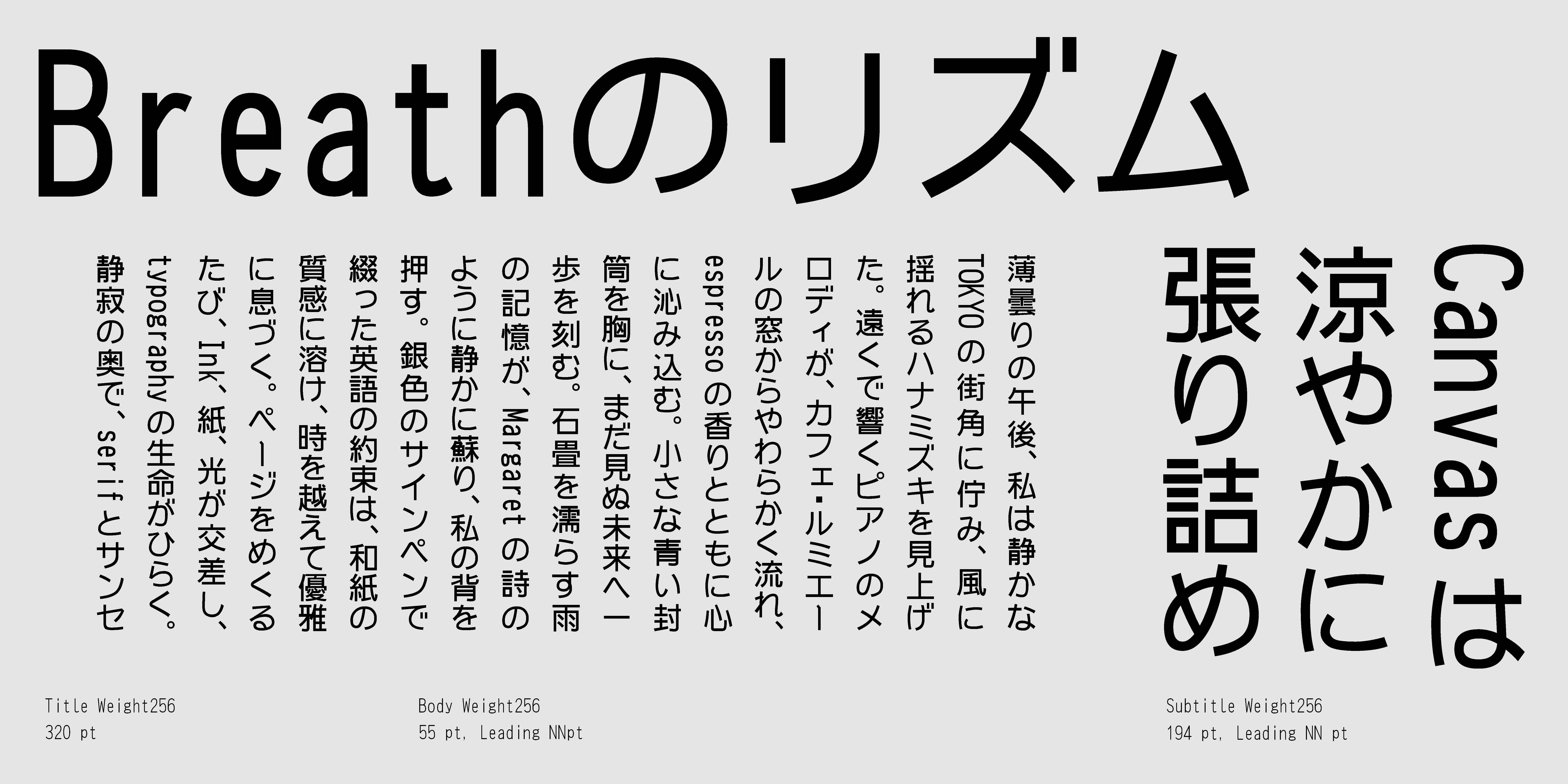
HGNewゴシック_RT
アプリケーション上で装飾加工した変形長体とは異なり、タテ線が「か細く」なっていない、可読性が高く見た目も自然な長体フォントです。文章の多い約款やモバイル製品の説明書など、狭い面積に多くの文字情報を詰め込むのに最適です。
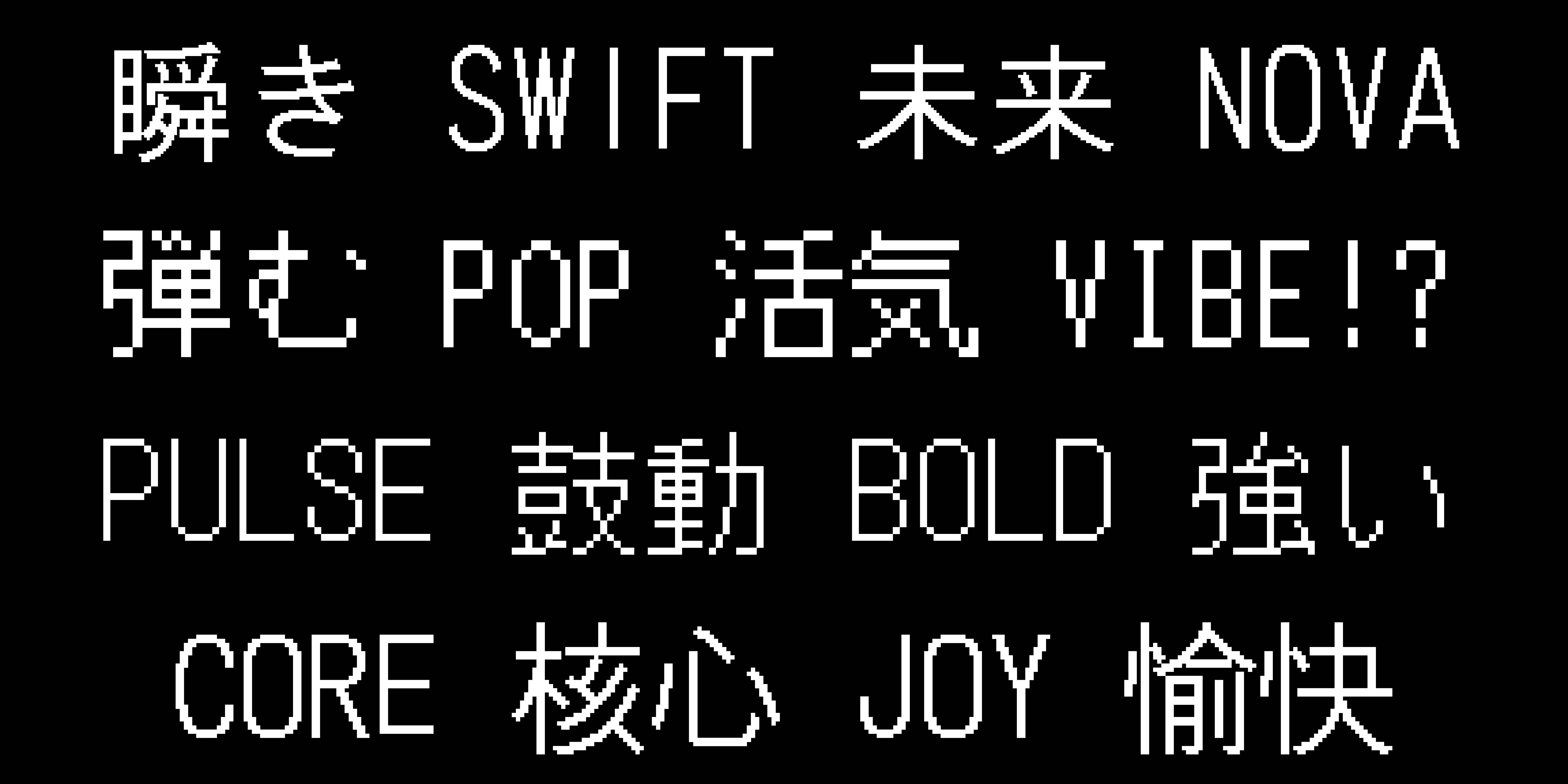
HGドットゴシック
ビットマップフォントのデザインをアウトラインでデザインした書体です。ビットマップフォントのデザインを拡大縮小して利用することが出来ます。レトロな雰囲気を表現したい方にお勧めです。このほかにも、ドットNewゴシックやドット丸ゴシックやドット明朝など、豊富なバリエーションで皆様のご要望にお応えできます。
リコーフォントは、4種類の文字幅のフォントが用意されております。
様々なシチュエーションでご利用可能となっております。